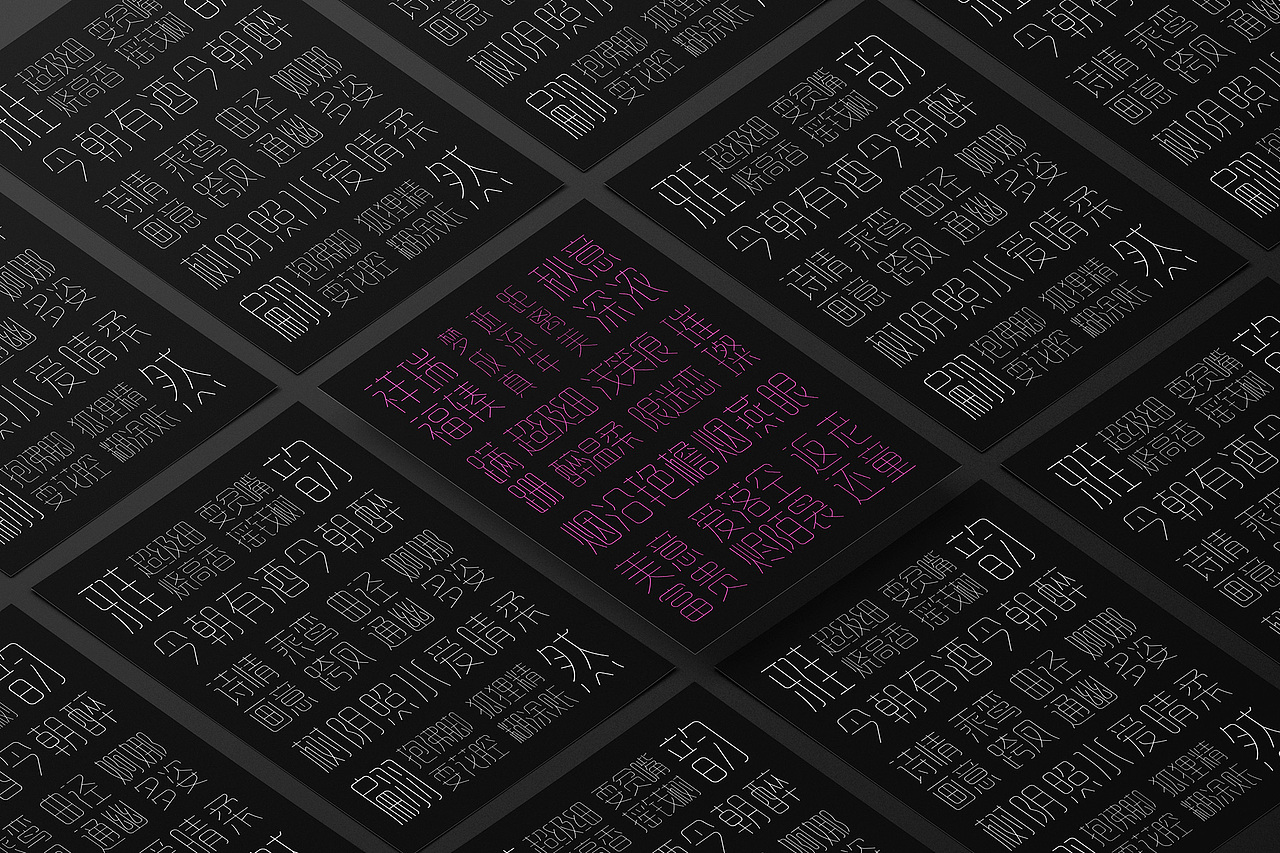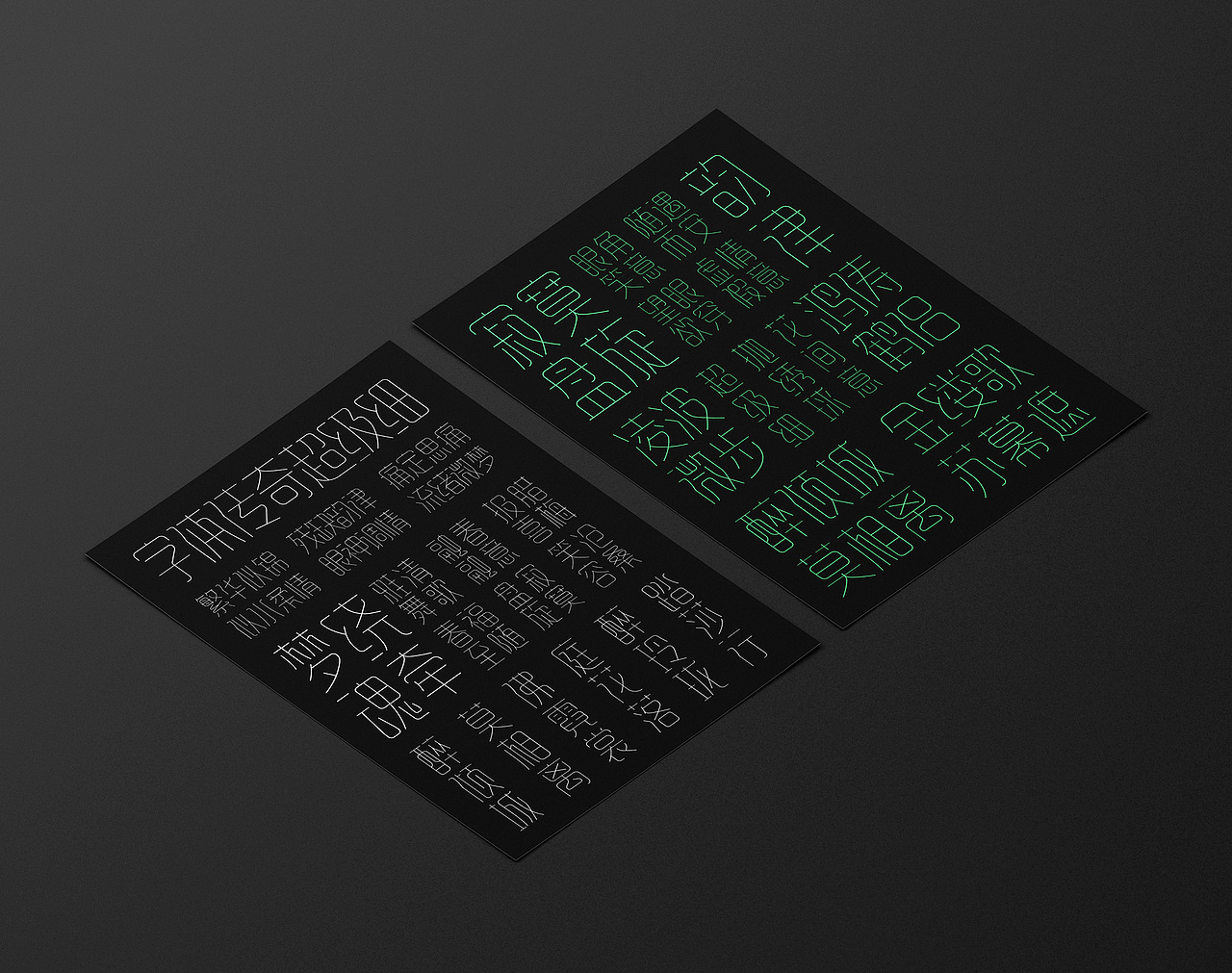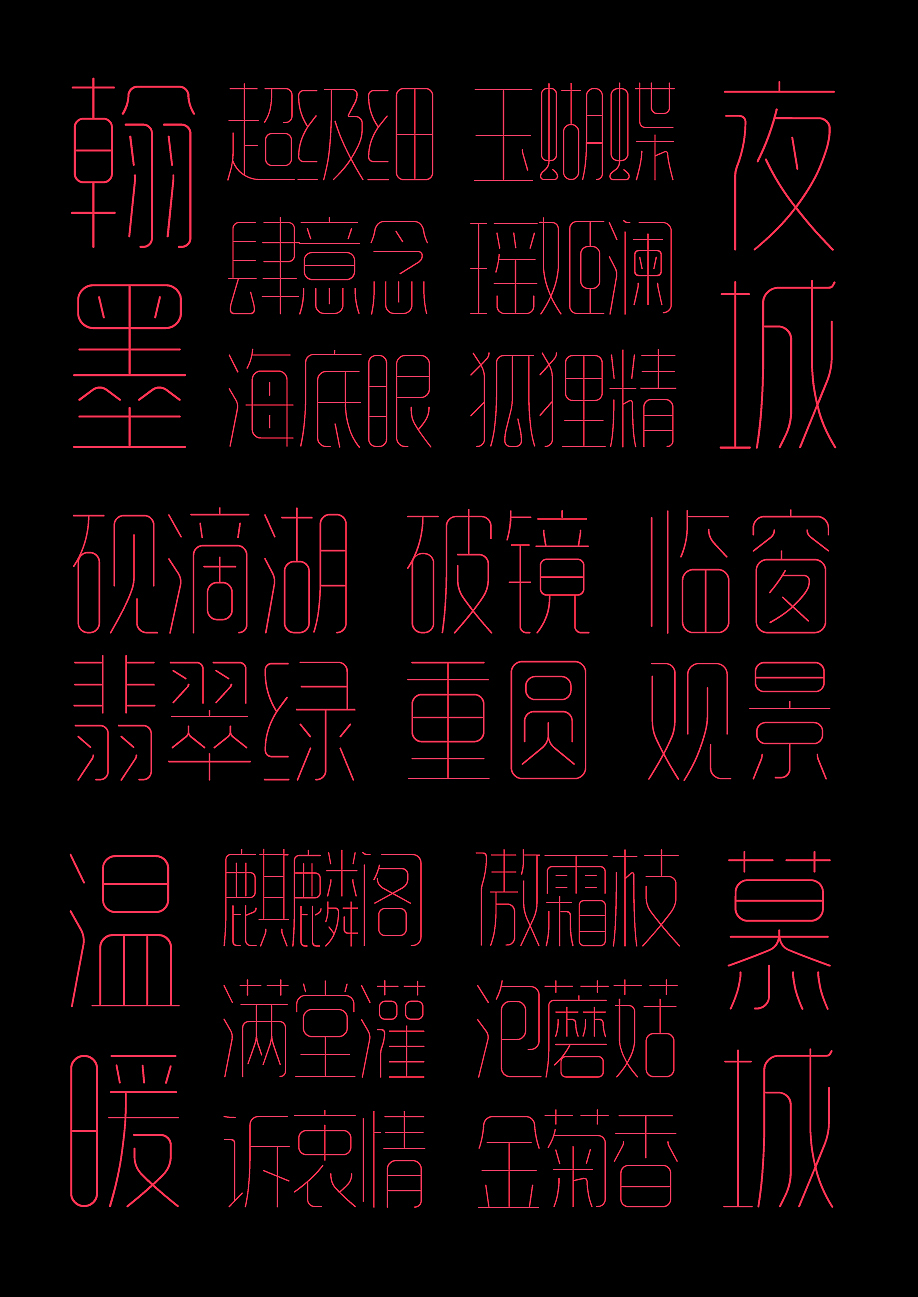
两款简约风格字库字体设计
字体传奇超级细
笔画细线设计,字形结构结合艺术字变形设计,整体简约唯美时尚,是一款微变形设计的字库,视觉统一,适用于字体标志,标题字体等。
字体传奇拂晓宋
字体设计简约轻盈唯美,横线笔画倾斜设计,撇捺笔画由粗到细变化,结构根据宋体进行修饰变形设计,适用于字体标志,标题字应用等。